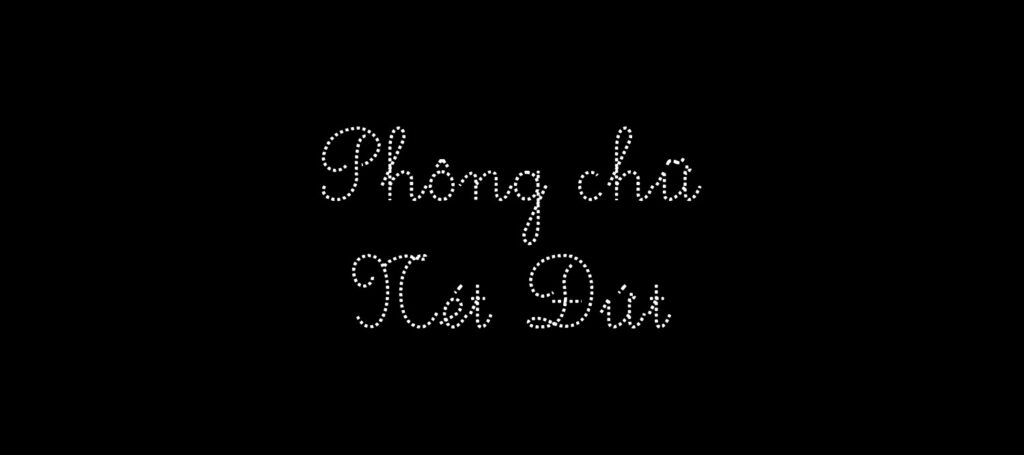
Font chữ nét đứt (Dashed/Dotted font) là công cụ chuyên dụng thường thấy trong các bản vẽ kỹ thuật để mô tả các thành phần ẩn, đường bao hoặc trong các tài liệu giáo dục tập tô. Việc tải font chữ nét đứt giúp các kiến trúc sư, kỹ sư và nhà thiết kế trình bày hồ sơ dự án một cách sinh động, phân cấp thông tin rõ ràng mà không gặp trở ngại về lỗi hiển thị.
Đặc trưng của dòng font chữ nét đứt trong trình bày thiết kế
Điểm nhận diện đặc trưng của dòng phông này chính là cấu trúc ký tự được tạo thành từ các đoạn thẳng ngắn hoặc các chấm tròn xếp liên tiếp nhau. Khác với phông chữ nét liền, phông chữ nét đứt mang lại hiệu ứng thị giác nhẹ nhàng, thường được dùng để đối trọng với các khối hình học vững chãi trong kiến trúc. Việc xử lý Việt hóa chuẩn giúp các dấu thanh phối hợp hài hòa với nhịp điệu đứt quãng của bộ chữ, duy trì sự mạch lạc cho văn bản ngay cả ở các chi tiết chú thích nhỏ.
Sự ổn định của các bộ phông này còn nằm ở khả năng hiển thị tương thích trên nhiều nền tảng phần mềm. Dù bạn sử dụng để làm mẫu chữ tập đồ cho trẻ em hay làm các đường chỉ dẫn trong AutoCAD, các nét đứt vẫn giữ được khoảng cách đồng đều. Đây là giải pháp phù hợp để thể hiện các ý tưởng sơ đồ, quy trình lắp ghép nhà container hoặc các hạng mục trang trí nội thất đòi hỏi sự tinh tế và phá cách.
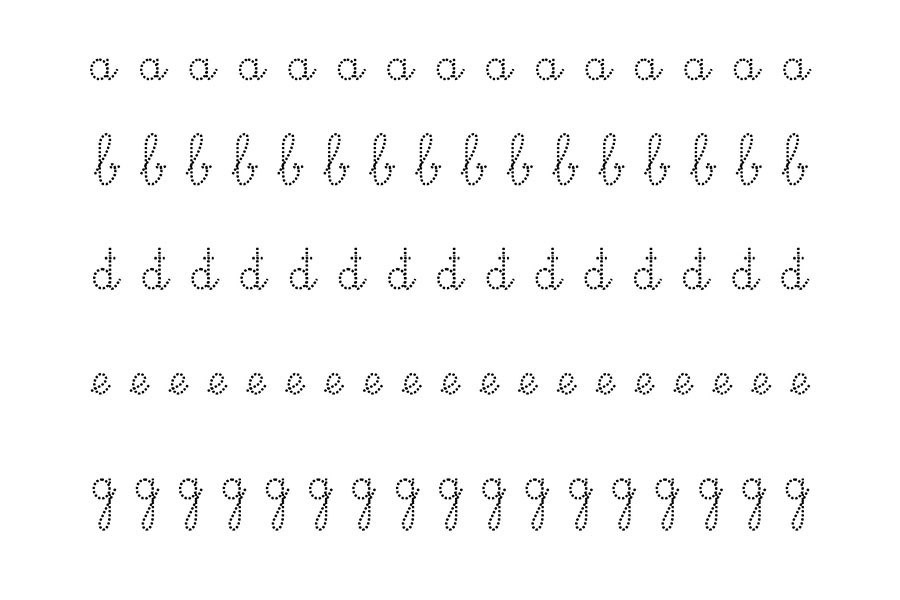
| Nhóm phông chữ | Đặc điểm thiết kế | Mục đích phù hợp |
|---|---|---|
| Dotted / Dashed Font | Nét đứt quãng, chấm bi, mảnh | Tài liệu học tập, sơ đồ ẩn |
Tư vấn lựa chọn: Nếu bạn đang chuẩn bị hồ sơ thuyết minh kỹ thuật, việc phối hợp font chữ nét đậm Việt hóa cho tiêu đề và font chữ nét đứt cho các phần chú thích ghi chú sẽ tạo nên sự tương phản chuyên nghiệp, giúp khách hàng dễ dàng theo dõi mạch logic của dự án.
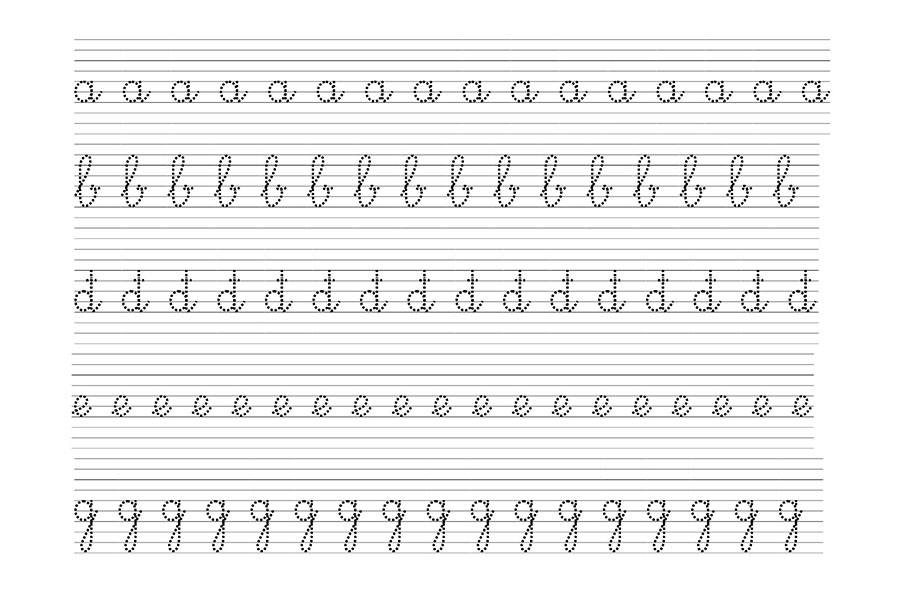
- Tính đồng bộ trong hệ thống ký hiệu: Hãy duy trì sự nhất quán giữa phông chữ nét đứt dùng trong sơ đồ và phông chữ nét liền dùng trong thuyết minh để hình ảnh thương hiệu của đơn vị thiết kế và thi công trông chuyên nghiệp hơn.